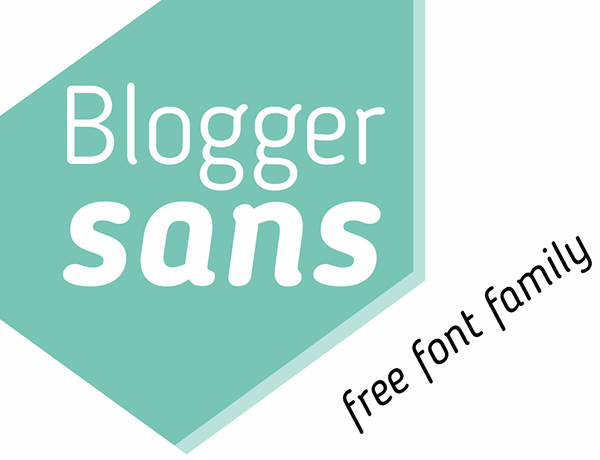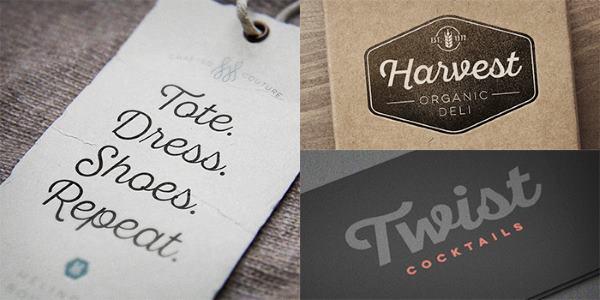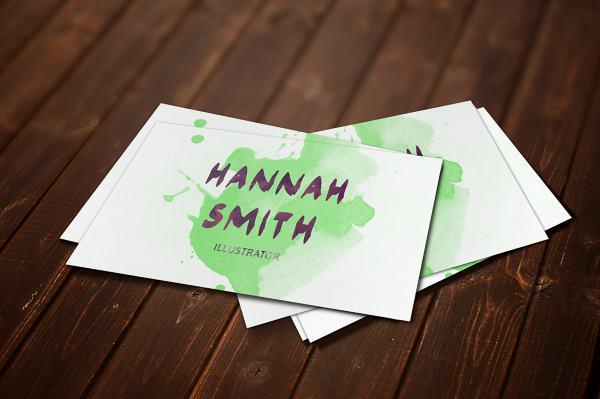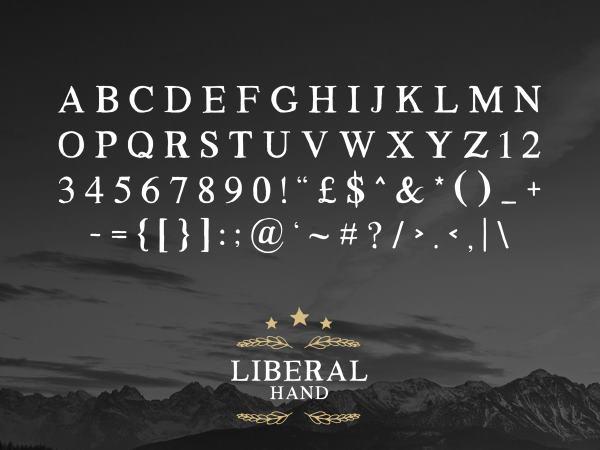
Didactic
Didactic, una fuente clara y limpia, que nos será de gran utilidad en trabajos donde el texto abunde y sea necesaria una lectura rápida y fácil.   Si se mira más a fondo podemos apreciar que posee hermosos detalles como la unión de los carácteres “t” e “i”, tal como se aprecia en la imagen.
Blogger Sans
Blogger Sans es una tipografía perfecta para trabajos semiformales por su diseño agradable y a la vez legible.  Tiene un ligero parecido con la fuente Dosis, que podemos encontrar en Google Web Fonts.
Sant’Elia
Una hermosa tipografía que tiene como objetivo el diseño gráfico ya que por su estilo nos vendrá como anillo al dedo en la confección de logotipos.   Tiene unas caractarísticas redondeadas y estilo manuscrito que son muy utilizadas en la confección de hermosas tarjetas de invitación, bautizos y similares.
Marziona
Este tipo de letra definitivamente es para diseños no formales. Simula trazos de pintura al óleo y quedan muy bien en panfletos, flyers o creaciones donde predomine la originalidad. Una bonita fuente que no se esperaba que fuera gratis por su calidad.
Liberal Hand
Una tipografía de corte clásico, con detalles que la hacen parecer media borrosa, como si fuese de máquina de escribir. En lo personal, está perfecta para documentos formales o diseños donde simulemos un medio de prensa antiguo.